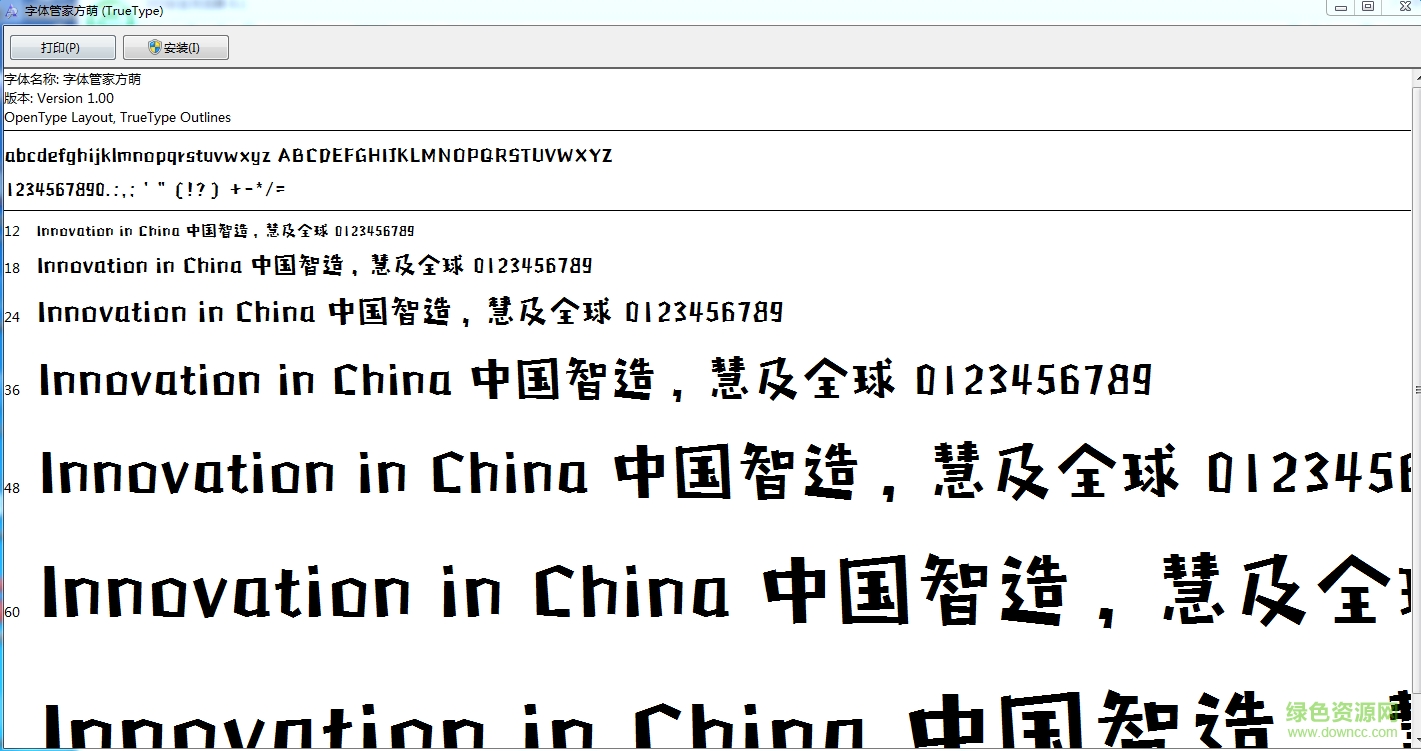
aa方萌字體
aafangmeng字體是一款萌萌的個性字體,風(fēng)格獨特,線條變化適度,有一點像小朋友寫的字,用在兒童讀本或平面設(shè)計方面效果不錯,喜歡的朋友快來綠色資源網(wǎng)下載吧!
漢字設(shè)計特點
1.從平面設(shè)計來講,漢字無疑是人類社會有史以來最偉大最成功的設(shè)計。它以最為簡單的設(shè)計元素,運用最豐富而復(fù)雜的設(shè)計手段,設(shè)計出了一件又一件恒定而單純的“產(chǎn)品”,并使這些產(chǎn)品的內(nèi)涵無比豐富、構(gòu)架無比完美、用途如此廣泛、影響如此深遠。
2.漢字的設(shè)計思想既高妙又單純,它實際上只以“點畫”兩種元素構(gòu)架而成;所謂的“永字八法”中,不同的筆畫式樣均可看成點畫的不同位置與樣式。